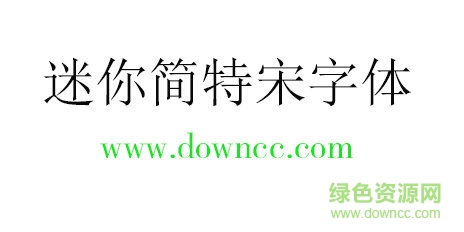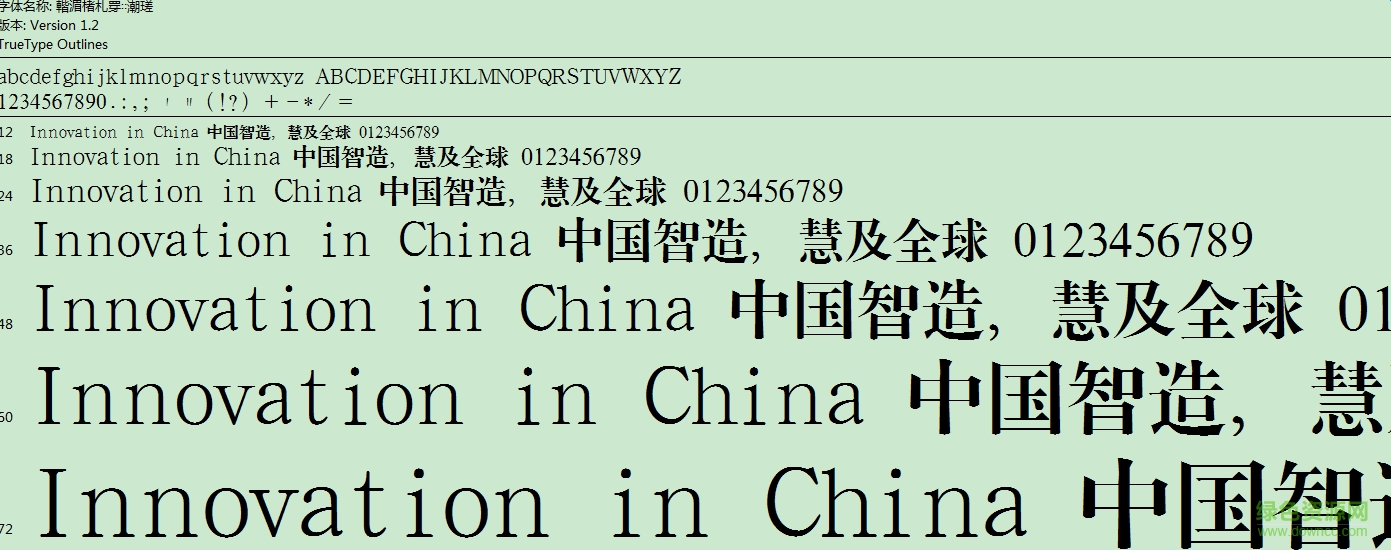
迷你簡(jiǎn)特宋是一款宋體字體的衍生版,主要表現(xiàn)為豎筆畫(huà)較粗,給人以成熟穩(wěn)重之感,適合作為標(biāo)題使用。小編為大家提供免費(fèi)下載地址。快來(lái)綠色資源網(wǎng)吧,有了這款字體就能讓你的書(shū)面文字排版更加美觀,給人一種賞心悅目的感覺(jué)哦,你可別錯(cuò)過(guò)了。